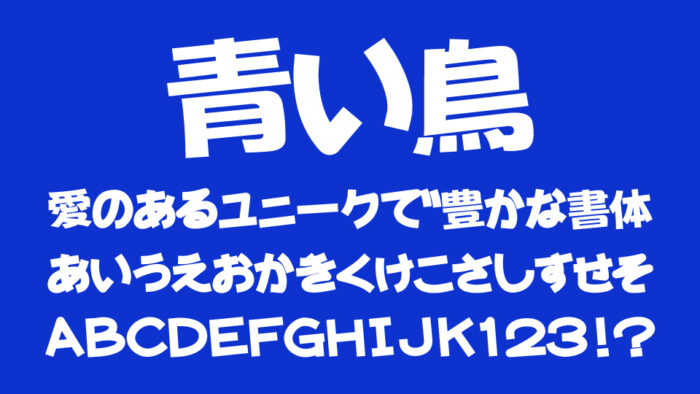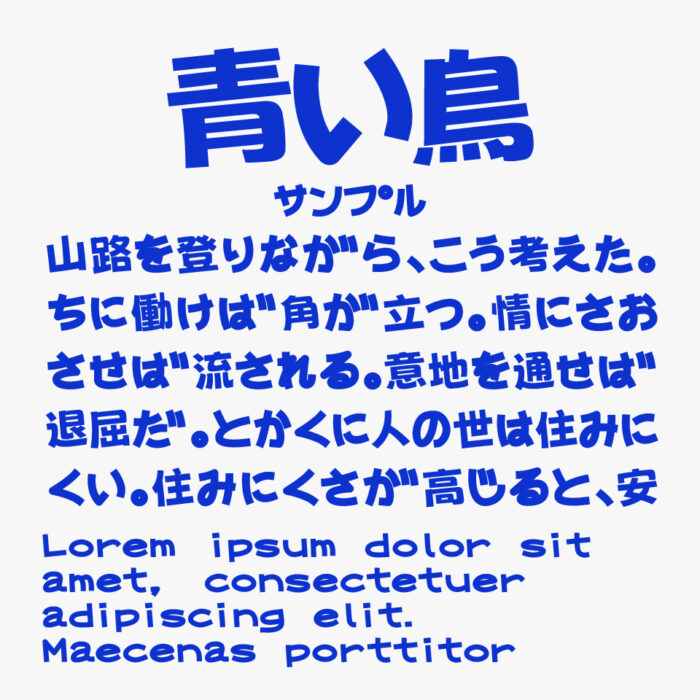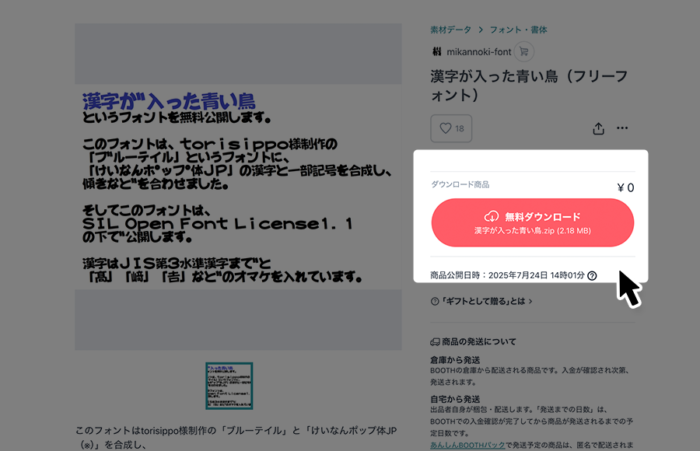
漢字が入った青い鳥フォントは、愛嬌のあるフォルム可愛らしい「ブルーテイル」フォントと「けいなんポップ体JP」フォントを合成して制作されたフォントです。
太く丸みを帯びた手書きらしさのある文字に、ほんの少しの跳ねや傾きが加わることで、元気いっぱいの表情のある可愛らしいフォントです。
漢字が入った青い鳥